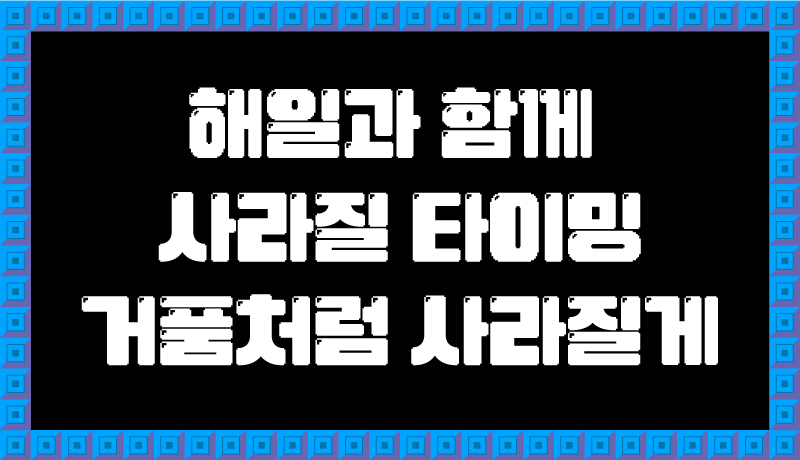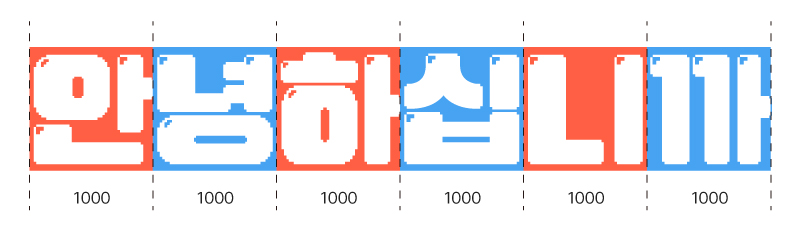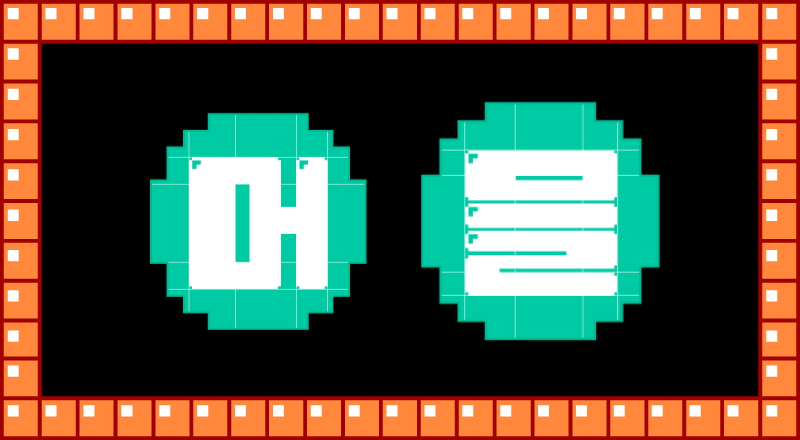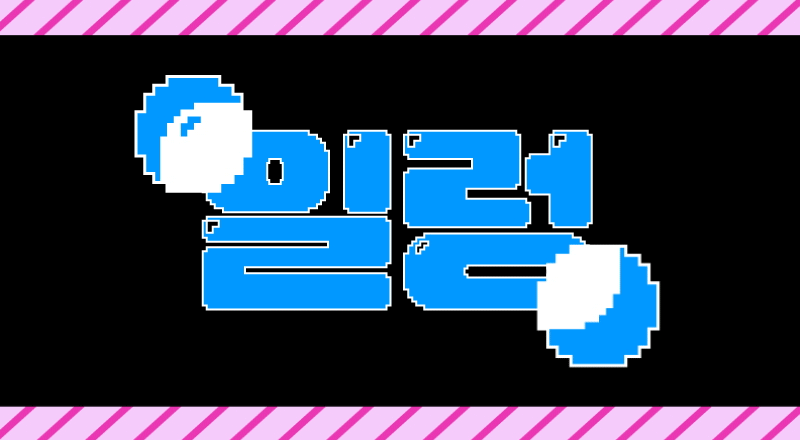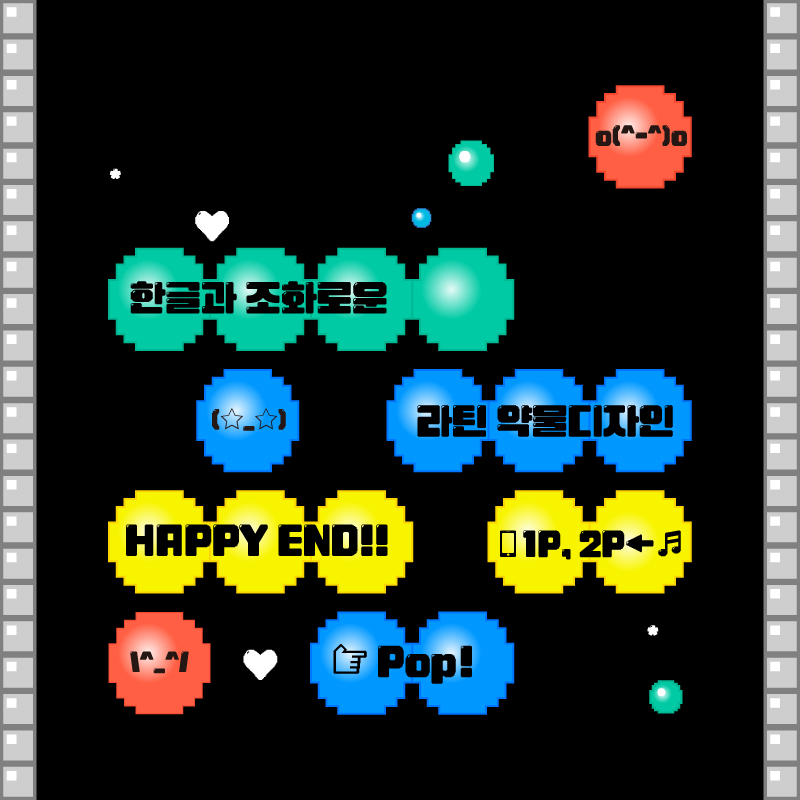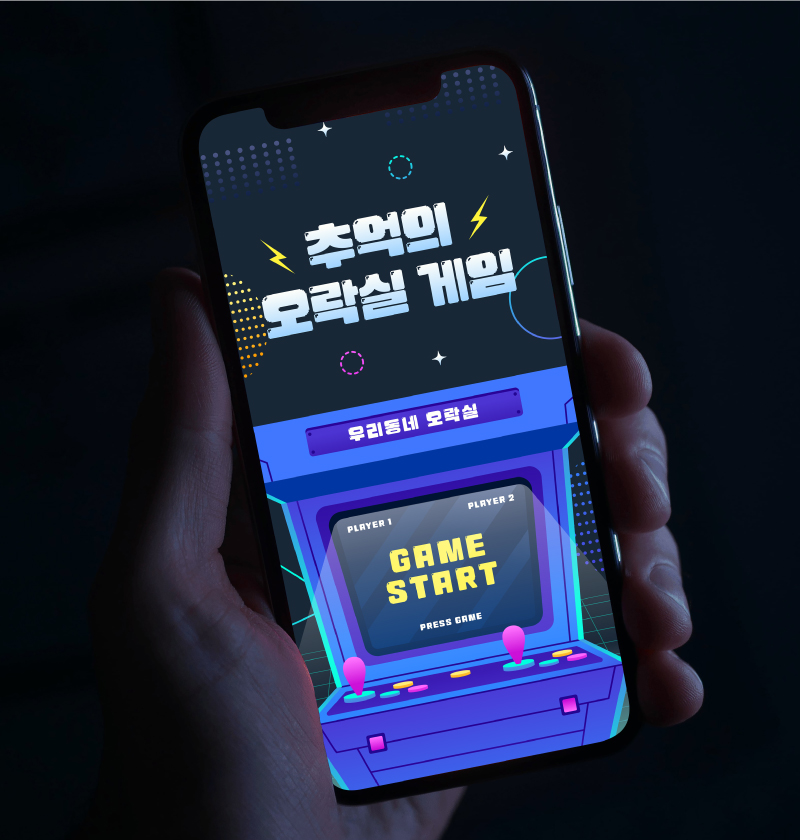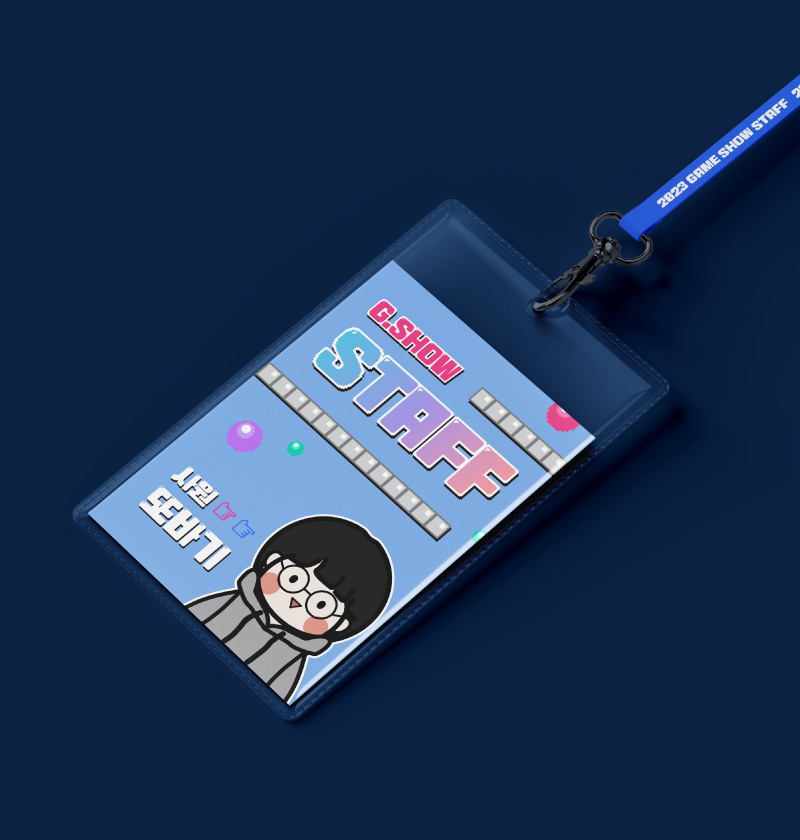
Rix버블
1 종 - Regular네모꼴 꽉 찬 형태와 두꺼운 획, 둥글둥글 꺾임이 귀여운 픽셀 폰트입니다.
불규칙한 획의 대비가 주는 리듬감과 자소의 디테일한 글레어 픽셀 표현이 특징입니다.
빵빵한 입체감과 버블리한 이미지가 돋보여 제목용 폰트로서 높은 주목도가 기대됩니다.
| 폰트구성 | 한글 2,350자 + 추가자 430자 / 라틴 94자 / 약물 986자 |